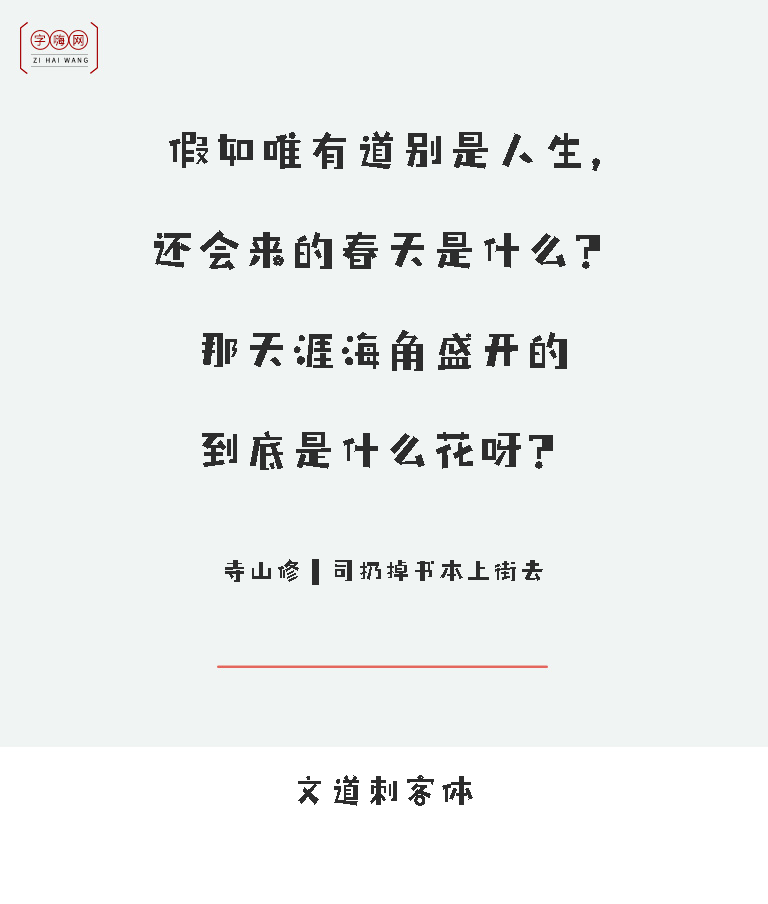
文道刺客体
简介: 【文道刺客体】这是一款可商用创意体,该字体在对每一笔画的粗细程度做了精心调整,使得任意一边的加粗程度都看上去恰到好处,而且每一笔画的整齐划一给其整体视觉带来一种全新美感,该字包含6763个中文、字母、符号和数字,适用于新媒体、电商、海报的标题和logo除了满足传统印刷媒介的标题,还适用于屏幕显示、短视频字幕和产品包装设计。